2023モリサワ新書体情報解禁!個性派揃いの今年のラインナップを一挙ご紹介します!
モリサワでは、毎年新書体をリリースしています。昨年はデザイン書体をはじめ、大幅に拡充したモリサワの書体ラインナップ。今年はさらに、バリエーションが広がる書体が追加されます。使いたい書体が見つかるはず…!
2023年のモリサワ新書体ラインナップはこちら!
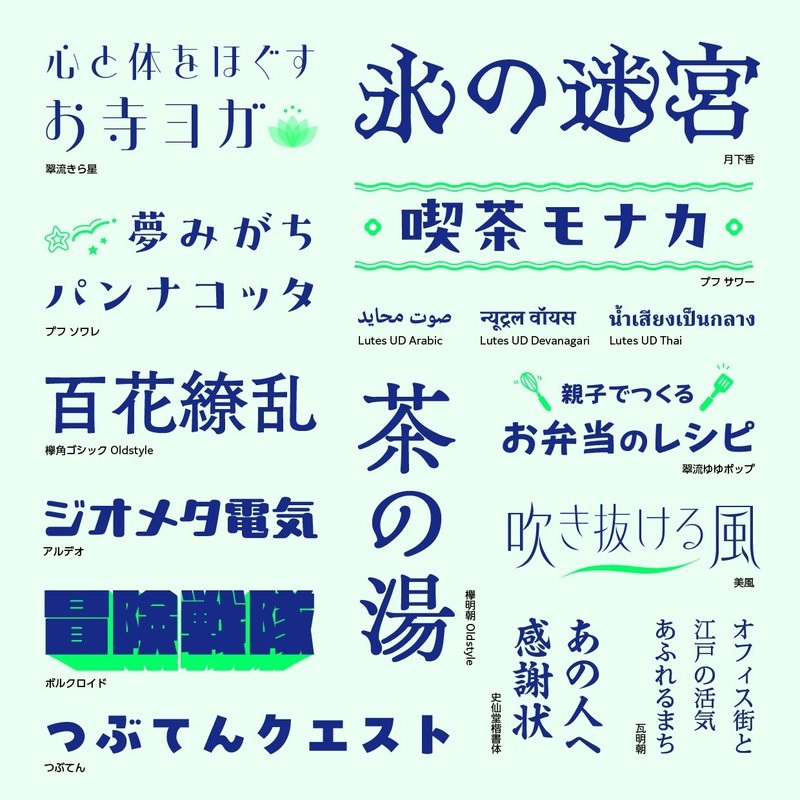
個性溢れる粒揃いの書体群になっておりますよ〜!早速新書体をそれぞれご紹介していきます!
一段と目を引く個性派デザイン書体たち
ボルクロイド
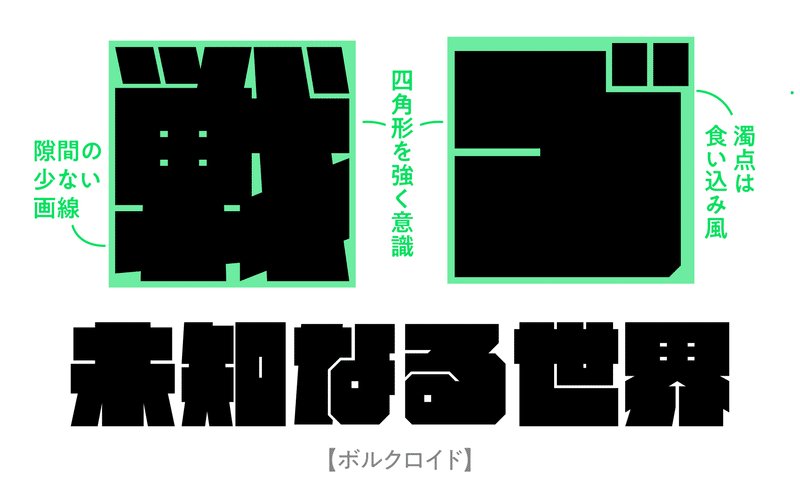
トップバッターは、「これ以上無理!白い部分がなくなっちゃう!」というくらい太い「ボルクロイド」です。見出し利用に特化した、硬質で力強いイメージのデザイン書体です。
直線のみで構成されていて、字面も大きく図形的なインパクトがあるので、漫画やアニメのタイトルやポスターの見出しなど大きく使うことで活躍する書体です。ロゴなど目を引きたい場面にぴったりです。
月下香
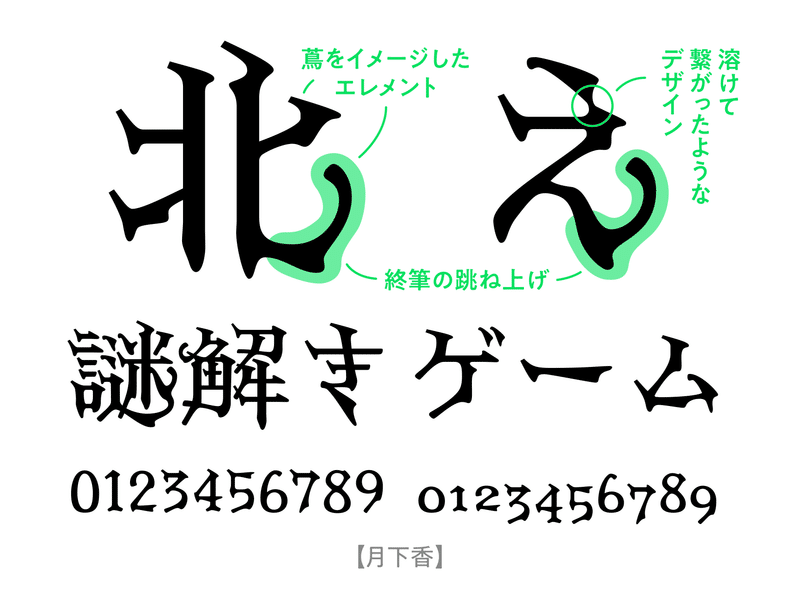
あえてアンバランスに設計された骨格、蔦のように上向きに伸びるハネやハライ…おどろおどろしい雰囲気を醸し出すこちらは「月下香」です。ミステリアスで非日常的な印象を与えるデザイン書体です。見出しで利用いただくことで、強く目を惹く効果を発揮します。
デフォルトのデザインの数字のほかに、画像右下のようなオールドスタイル数字(※1)を搭載しています。アプリケーション上のOpenType機能を使って呼び出すことで、よりレトロな雰囲気を演出することもできます。
※1【オールドスタイル数字】アルファベットの文字の中に入っても自然に本文となじむよう、上下のラインに変化をつけた数字。
アルデオ
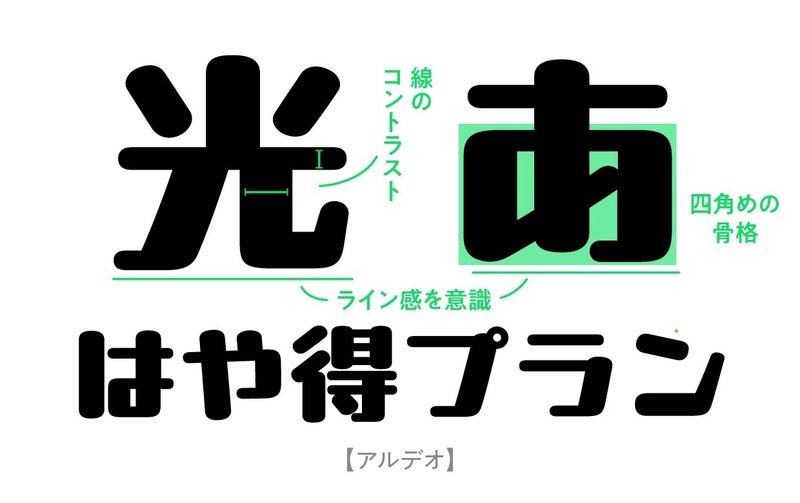
「アルデオ」は、直線で構成された幾何学的な骨格に丸みのあるエレメントを組み合わせたデザイン書体です。水平垂直のラインを意識したやや平体気味のプロポーションやコントラストのある画線が特徴で、インパクトがありながらも親しみやすい表情を演出します。
広告やコミック、ロゴなど、目を引きたいシーンで活躍する書体です。
つぶてん
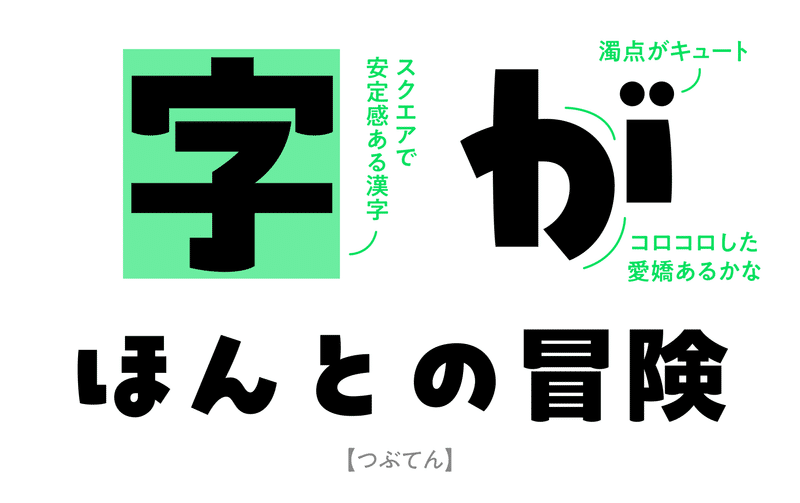
「つぶてん」は明るく元気な印象の見出し向けの太ゴシック風デザイン書体です。安定感のある漢字に、字面が小さく可愛らしい印象のかなを合わせています。可愛らしさと真面目さのバランスが絶妙な書体です。
「つぶてん」の書体名は「礫」に由来していて、石のようなコロコロ丸い濁点もかわいいポイントです。
金属活字からインスピレーションを受けた、オールドスタイルの兄弟書体
欅明朝 Oldstyle
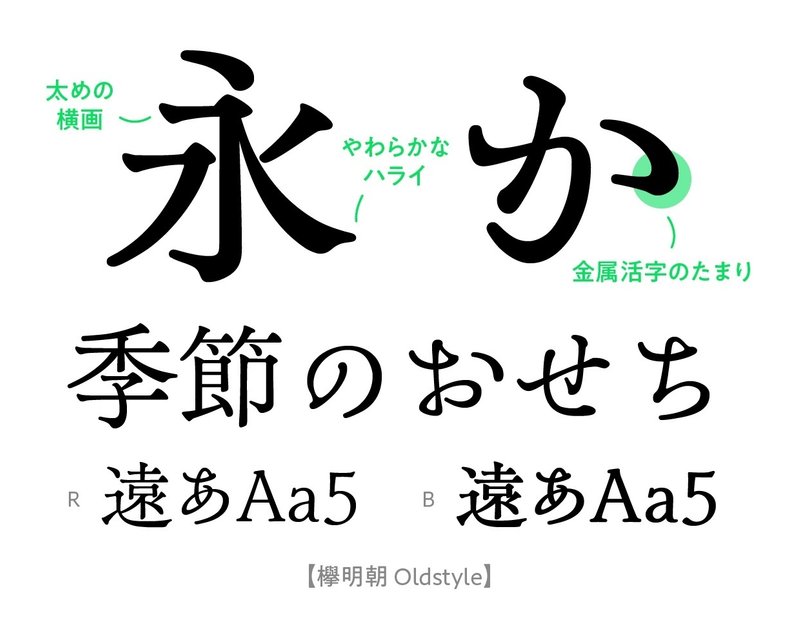
続いては「欅明朝 Oldstyle」です。上品でやわらかな印象のオールドスタイルの明朝体です。“オールドスタイル”とは、ふところがきゅっとしまっていて、伸びやかなハライが特徴のスタイル。手で書いたような運筆の有機的な要素を取り入れています。
画像のように、欅明朝の収筆や折り返し部分を見てみると金属活字由来のインクの溜まりを再現した丸みがあります。これが柔らかい印象につながっているんですね。
RとB、2つのウエイトで展開しています。
欅角ゴシック Oldstyle
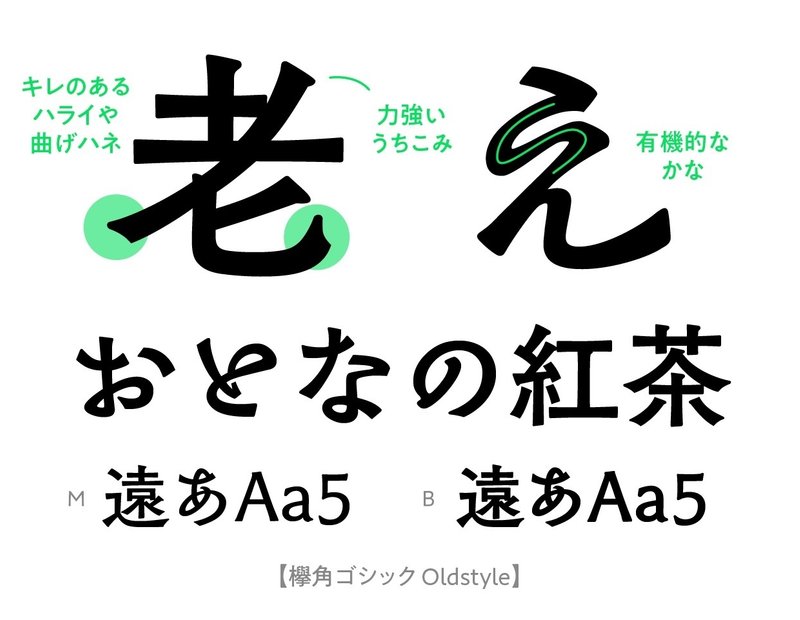
「欅角ゴシック Oldstyle」は「欅明朝 Oldstyle」と同一のコンセプトと骨格をもつオールドスタイルのゴシック体です。ゴシック体でも、金属活字由来の骨格とインクの溜まりを再現したエレメントであたたかな印象です。
かなは自由な運筆で抑揚があり、MとB、2つのウエイトで展開されています。
2022年登場のプフシリーズに新しい書体が仲間入り♡
プフ サワー
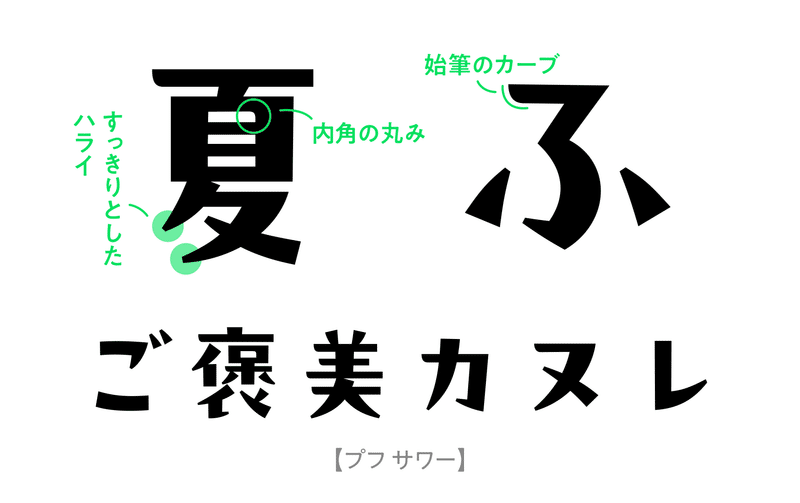
2022年に初登場した「プフ」シリーズ。統一しすぎない自由な字形と小さめの字面が特徴のデザイン書体ラインナップです。2023年の「プフ」は、より大人な印象になって登場です。
「プフ サワー」はすっきりとしたハライを持つハイコントラストなデザインで、パッケージや書籍の装丁などにもってこいです。レトロな雰囲気を醸し出します。
プフ ソワレ
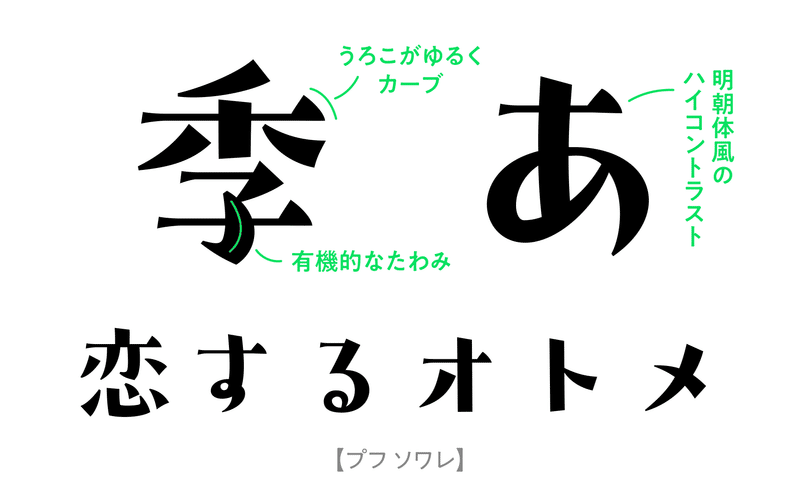
「プフ ソワレ」はかわいらしさとエレガントさを兼ね備えた明朝体風のデザインです。こちらもパッケージや書籍の装丁、動画のテロップなど幅広い場面でお使いいただけます。
そしてこのプフシリーズ、遊び心たっぷりの仕掛けがあります。書体ごとに “オリジナルキャラクター絵文字” を1文字搭載していて、異体字として選択入力ができるんです。「プフ サワー」「プフ ソワレ」にはこんな子達がいますので、リリースされましたら皆さまお手元で変換してみてくださいね…♡
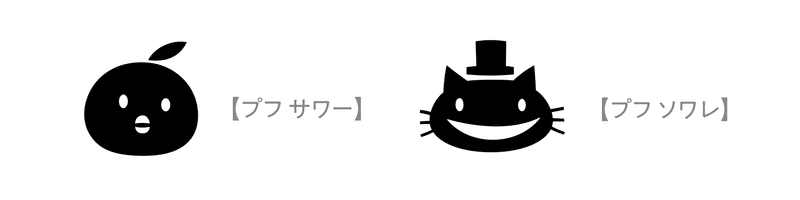
繁体字フォントをベースに開発された、トレンド感あふれる和文デザイン書体
美風
こちらは、風・舞い落ちる葉・揺れるススキなど自然をモチーフにして設計されたデザイン書体「美風」です。
長体の骨格と繊細でシャープなラインが特徴です。水平垂直に整備された縦画・横画と、ハライや点画に見られる滑らかな曲線のエレメントの組み合わせは、涼やかで洗練された印象を与えます。
ちょうど今の季節にぴったり…(初夏に執筆しています)
「美風」は台湾のデザイン事務所「玉川設計所」が手掛ける繁体字フォント「風體 Wind Font」をベースに制作しています。
翠流きら星
「翠流きら星」はモダンで可愛らしい印象のハイコントラストなデザイン書体です。長体ぎみのプロポーションと極細の横画やハライが繊細な印象を与え、円や半円の点は遊び心を感じさせます。
モリサワで制作したかな・英数字に、台湾のタイプファウンダリー「Arphic Types」の「AR白玉書体」の漢字を組み合わせています。「翠流」という接頭辞がその印です。
翠流ゆゆポップ
続いても「翠流」シリーズ。「翠流ゆゆポップ」は、太い平芯のマーカーペンで書いたような、親しみやすく楽しげな雰囲気を持つPOP体です。適度にアンバランスな文字のプロポーションが、楽しさやホッとするような優しさを感じさせます。
絵本やテロップ・POPなどの幅広い場面でお使いいただけます。「翠流ゆゆポップ」はモリサワで制作したかな・英数字に、Arphic Typesの「AR悠々ゴシック体EB」の漢字を組み合わせています。
新聞・賞状で使われる専門書体がフォント化!
瓦明朝
毎日新聞社が開発した、モダンテイストの明朝体です。実際に新聞紙面の見出しとして使われている書体をベースにしています。
「瓦明朝」の「瓦」は「瓦版」(※2) に由来します。
コントラストが低く、横画やハライの先端も太めに設計されており、視認性が高いデザインになっています。
※2【瓦版《かわらばん》】江戸時代、天災地変・火事・心中などの事件を速報記事にして街頭で売り歩いた印刷物。ふつう半紙一枚刷り。原版として木版が残るが、もとは粘土に文字や絵を彫り、瓦のように焼いて作ったという。読み売り。
史仙堂楷書体(字游工房)
「史仙堂楷書体」は、筆耕士(※3)・信長宏氏の文字をフォント化した太楷書体です。40年以上の経験に裏打ちされた筆の息遣いが、力強く活き活きとした印象の中に品位や信頼感を感じさせます。賞状や証書はもちろん、商品パッケージや、目を惹きつける見出しなど大きなサイズでの使用に適しています。
※3【筆耕士】表彰状や感謝状、宴会の献立や座席札などを毛筆で書くことを職業とする人。
多言語セリフ書体が初登場!
Lutes UD Arabic / Devanagari / Thai
モリサワのラインナップにアラビア文字・デーヴァナーガリー・タイ文字のセリフ書体が追加されました。
「Lutes UD Arabic / Devanagari / Thai」は欧文フォント「Lutes UD PE」の多言語展開として作成されたフォントです。
「Lutes UD PE」はデジタルデバイス上での視認性に配慮した、ローコントラストでありながらもクリアですっきりとした印象のセリフ体で、「Lutes UD Arabic / Devanagari / Thai」にもその特徴を反映しています。
アラビア文字・デーヴァナーガリー・タイ文字で展開する際に、「Lutes UD PE」と併用してデザインの統一性を持って組むことができます。
あとがき